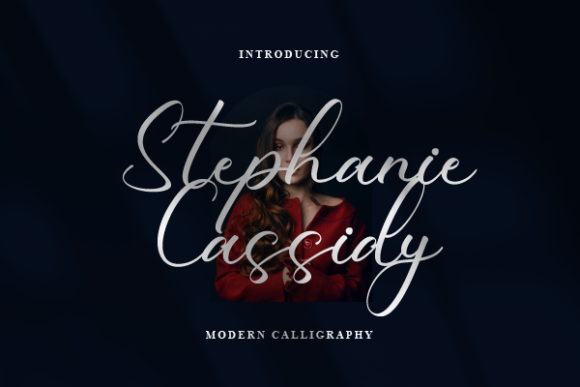
Stephanie Cassidy
適切なデザイン要素を見つけるのは難しい場合がありますが、Stephanie Cassidyは作品を即座に引き立てる優れたコレクションを提供します。
POD(オンデマンド印刷)製品、結婚式の招待状、またはソーシャルメディアのグラフィックを作成している場合でも、Stephanie Cassidyは理想的です。